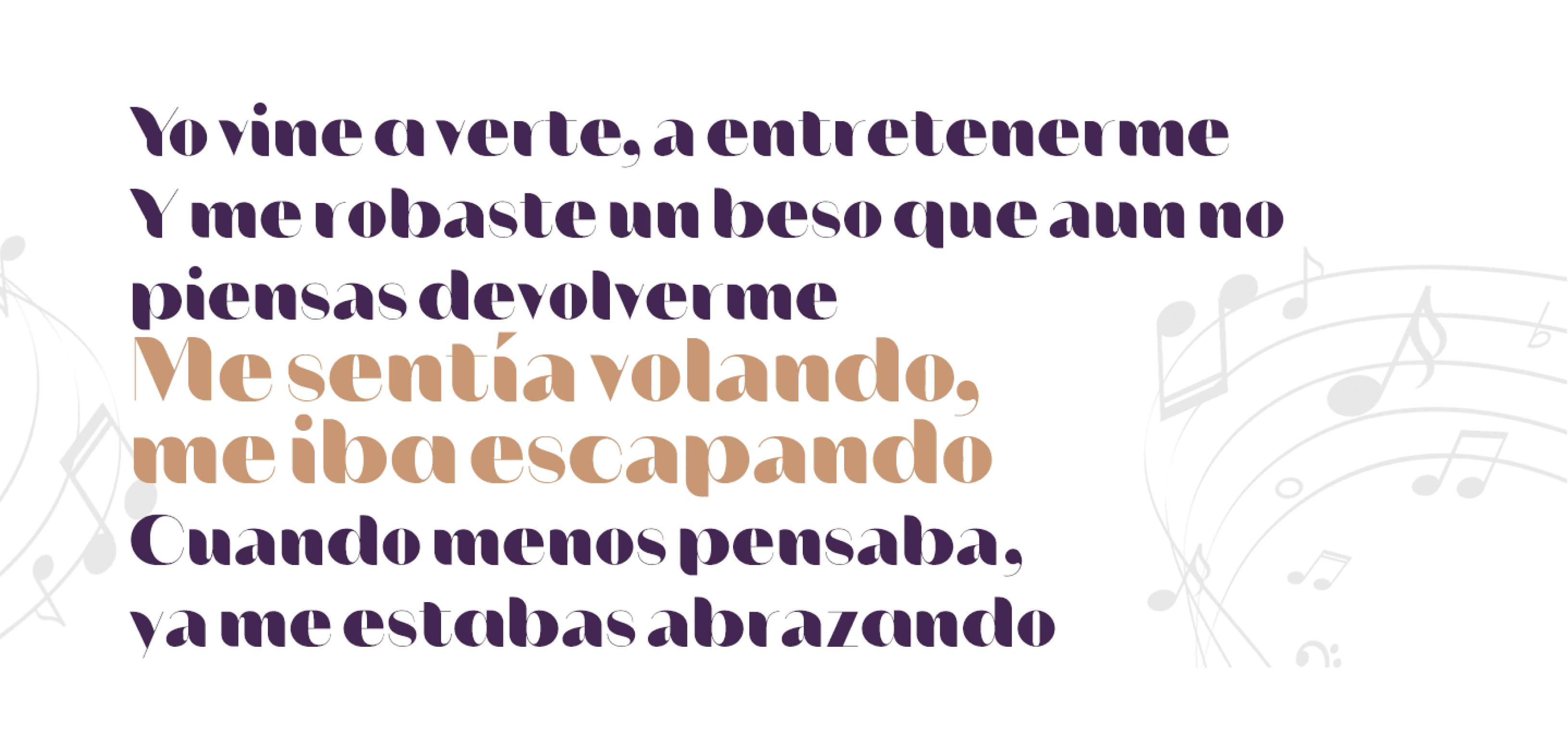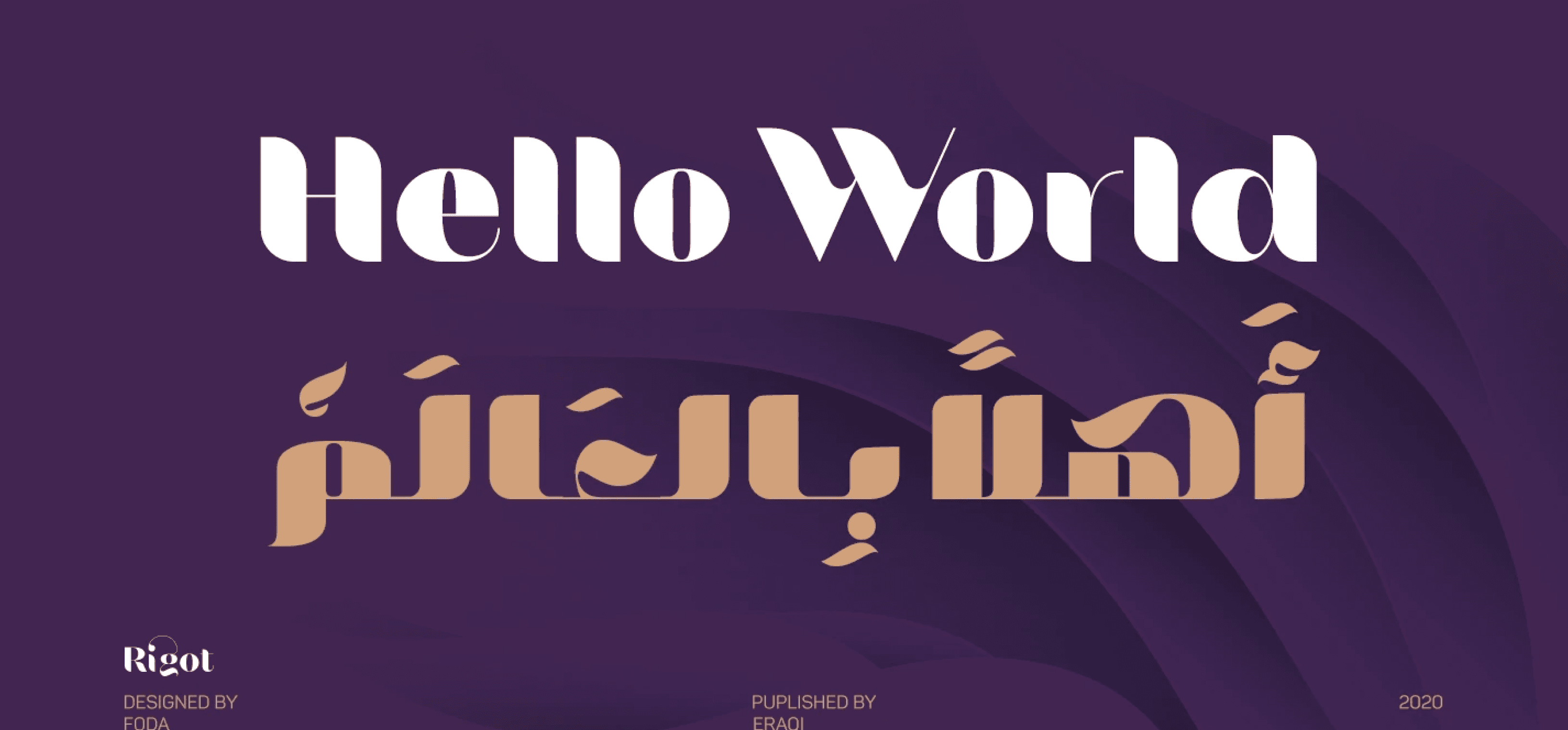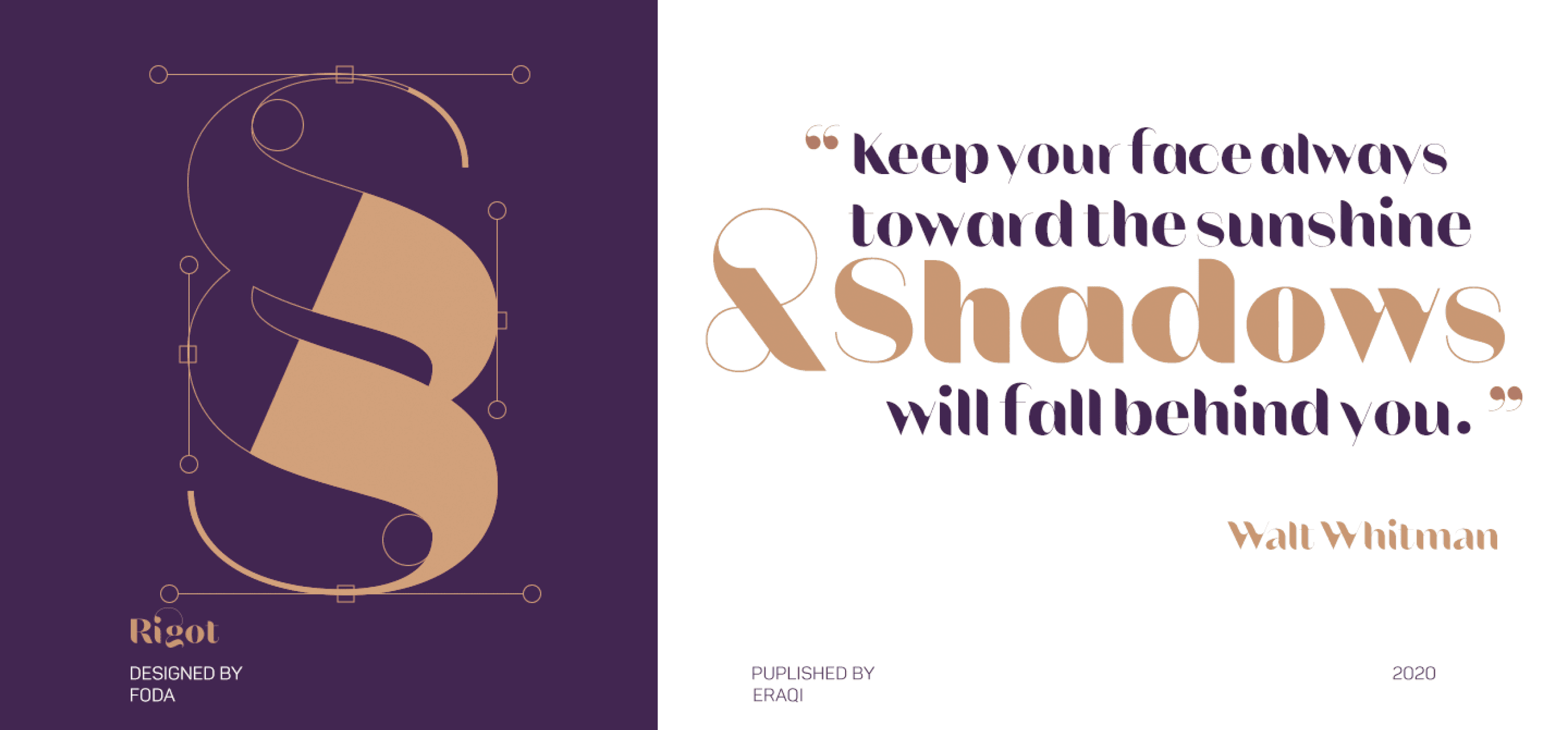
هو خط عرض عصري، يتوفر بوزنين: عادي (Regular) وعريض (Bold)، ويتميز بمجموعة موسعة من الحروف اللاتينية الإضافية تضم 552 رمـزًا (Glyph)، مما يتيح دعمًا لعدة لغات، بالإضافة إلى دعم كامل للغة العربية.
يتضمن الخط ميزات متقدمة في صيغة OTF مثل التراكيب القياسية والاختيارية، والبدائل الأسلوبية، وغيرها من الخصائص.